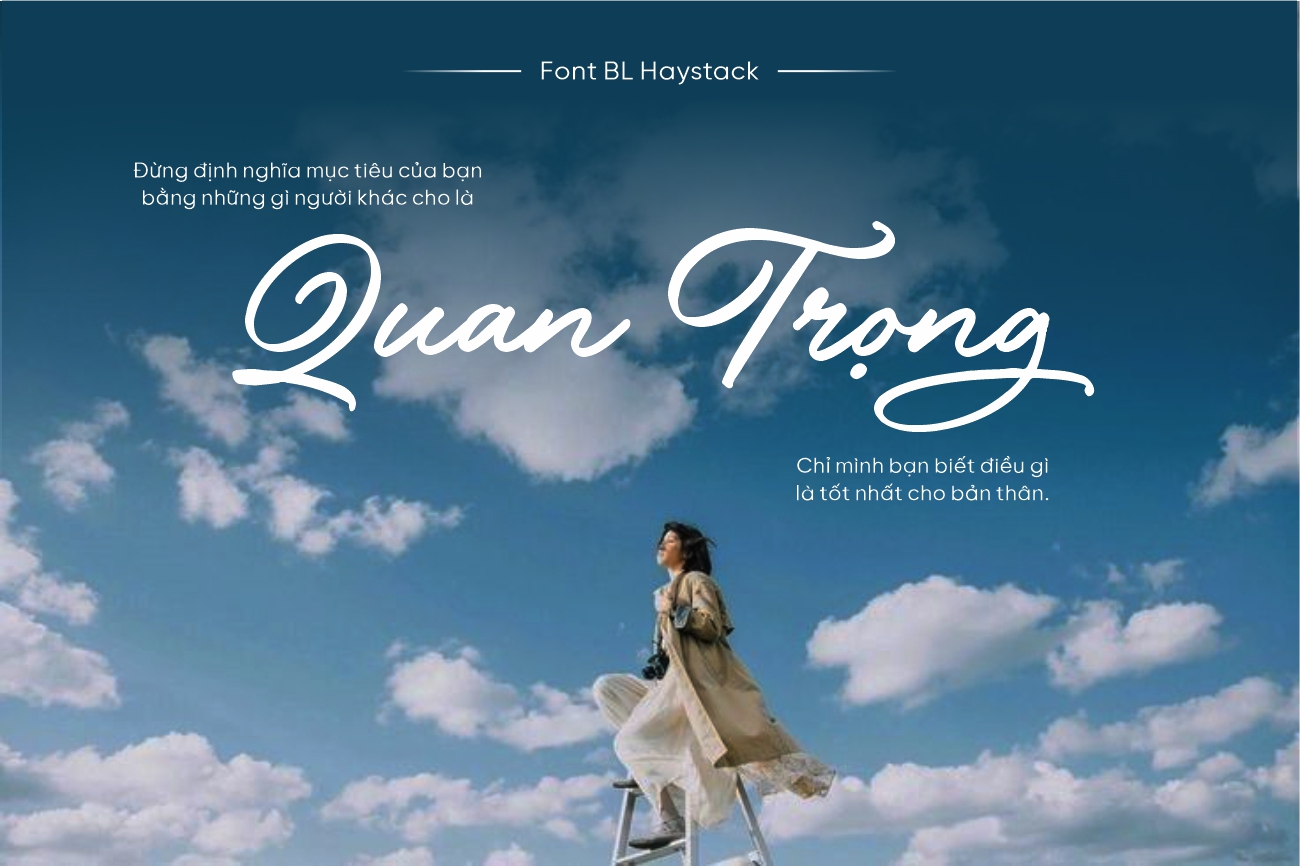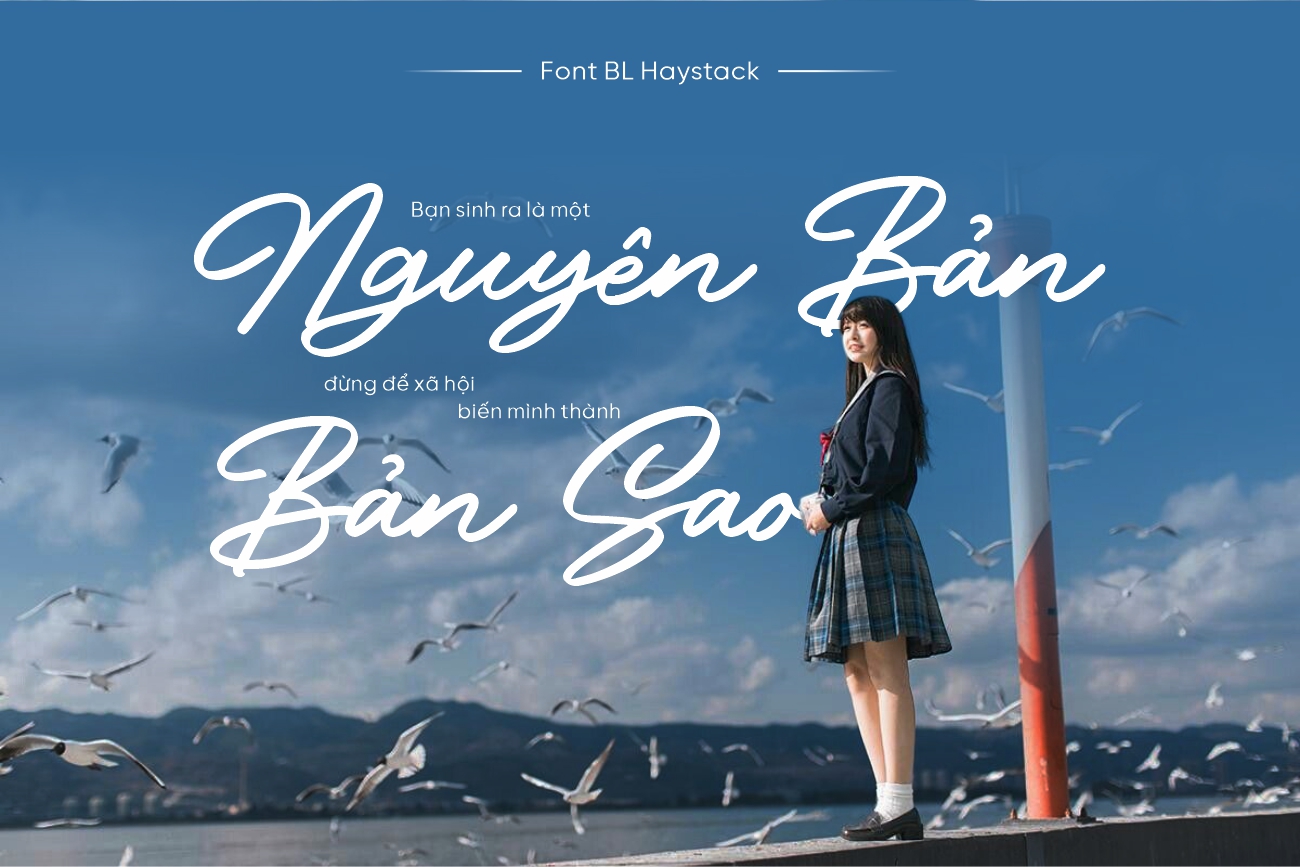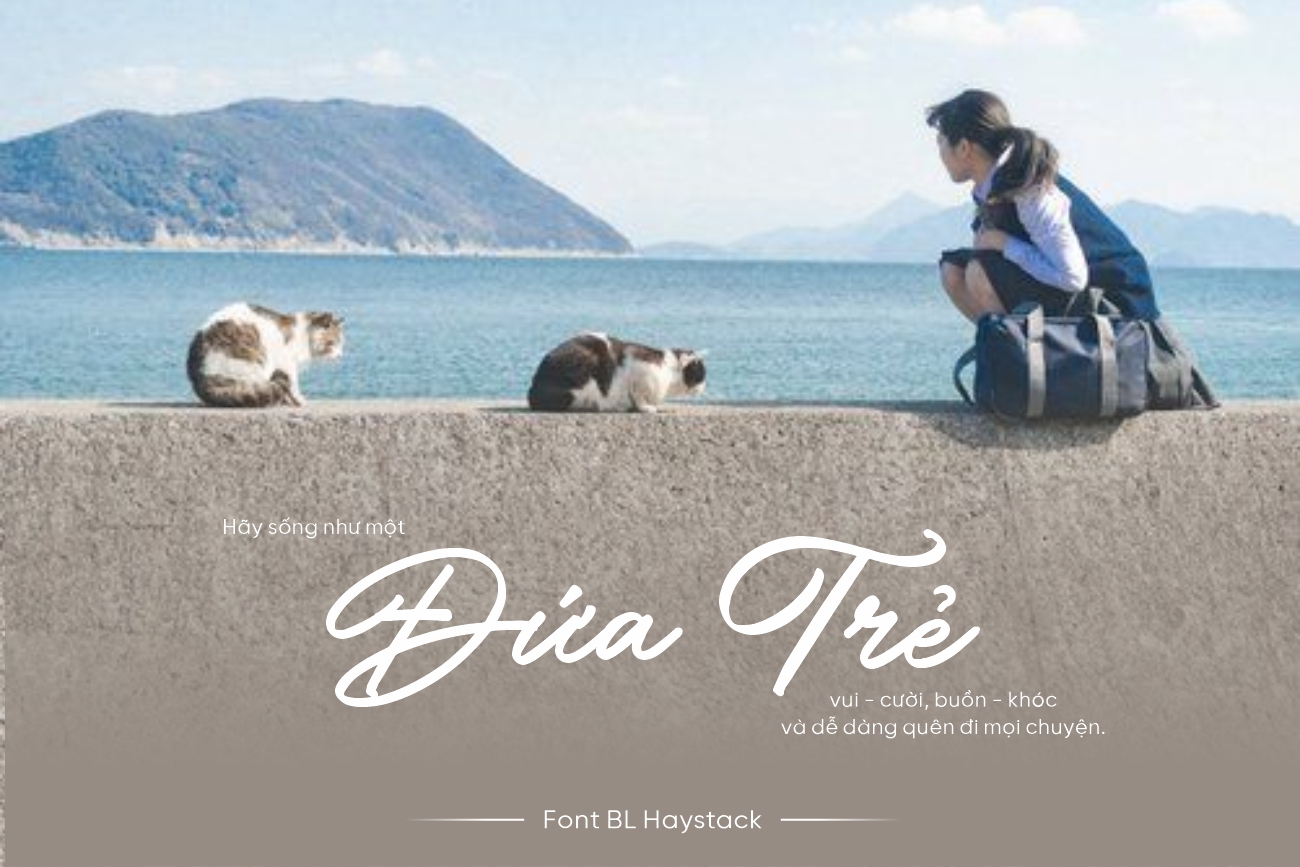
BL Haystack - Font brush mạnh mẽ
BL Haystack là phiên bản Việt hóa từ bộ font Haystack do Hendry Juanda thiết kế, mang đậm hơi thở nghệ thuật hiện đại với sự kết hợp hài hòa giữa sự phóng khoáng và tinh tế. Ngay từ lần nhìn đầu tiên, bộ chữ gây ấn tượng bởi tinh thần của một font brush mạnh mẽ, thể hiện cá tính rõ rệt nhưng vẫn giữ được nét thanh lịch, sang trọng và mềm mại rất cuốn hút. Phiên bản BL Haystack do Team BL Việt hóa được chăm chút kỹ lưỡng, tối ưu khả năng hiển thị tiếng Việt với đầy đủ dấu, giữ nguyên sự uyển chuyển của từng nét bút nhưng vẫn đảm bảo độ cân bằng trong bố cục. Nhờ vậy, người dùng Việt có thể tận dụng trọn vẹn vẻ đẹp cảm xúc và tính thẩm mỹ cao mà bộ font mang lại trong nhiều loại thiết kế khác nhau.
Về kiểu dáng, BL Haystack được phát triển theo phong cách kiểu dáng viết tay, mô phỏng từng đường lướt của cọ vẽ trên nền giấy, mang lại cảm giác chân thật và đầy cảm xúc. Các nét chữ có độ dày mỏng uyển chuyển, vừa phóng khoáng vừa mềm mượt, tạo nên tổng thể chữ không chỉ đẹp về mặt thị giác mà còn tạo cảm giác cá nhân, gần gũi như những dòng chữ được viết bằng tay đầy tâm trạng. Sự linh hoạt này giúp bộ font trở nên thu hút và có tính nghệ thuật cao, phù hợp cho các thiết kế cần chiều sâu cảm xúc, từ logo thương hiệu, poster, bao bì sản phẩm, social media cho đến thiệp cưới, thiệp chúc mừng hay các dự án sáng tạo mang tính cá nhân hóa.
Nguồn gốc cảm hứng của Haystack đến từ những nét chữ mang tính biểu đạt mạnh mẽ nhưng vẫn mềm mại, giống như sự hòa quyện giữa cảm xúc nghệ thuật và sự tinh tế hiện đại. Khi được Team BL Việt hóa thành BL Haystack, bộ font không chỉ giữ nguyên tinh thần sáng tạo đó mà còn trở nên thân thiện hơn với môi trường thiết kế Việt Nam.
Nếu bạn đang tìm kiếm một bộ chữ vừa mang chất font brush mạnh mẽ, lại đủ thanh lịch, sang trọng và mềm mại, sở hữu kiểu dáng viết tay đầy cảm xúc, tạo cảm giác cá nhân, đồng thời thật sự thu hút và có tính nghệ thuật cao, thì BL Haystack chắc chắn sẽ là lựa chọn ấn tượng giúp nâng tầm cảm xúc và giá trị thẩm mỹ cho bất kỳ dự án thiết kế nào.